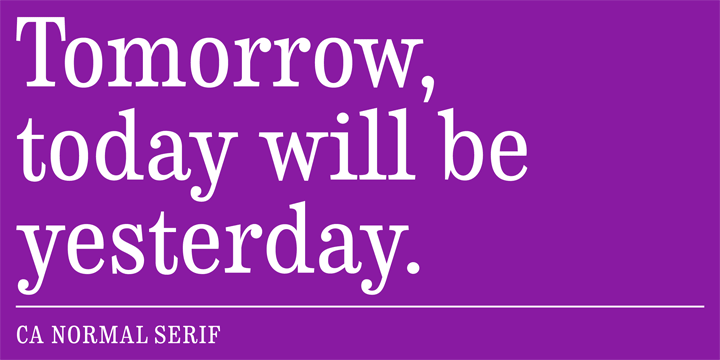
CA Normal bekommt einen Serifen-Bruder, bis 11.8. 50% billiger
CA Normal von der Cape Arcona Type Foundry erhält nun einen Freund/Bruder/Gegenspieler: CA Normal Serif. Anders als bei vielen anderen Meta Familien ist die Normal Serif aber weder eine Renaissance Antiqua, noch wurden wie so oft einfach Serifen an die Groteske angeklebt. Normal Serif bewegt sich irgendwo zwischen Scotch Roman und Slab Serif. Die Einflüsse liegen definitiv im 19. Jahrhundert und bei den Zeitungsschriften von Chauncey Griffith.
Auch ist die Verwandtschaft zwischen der Serif und der Grotesk Normal eher weniger offensichtlich. Trotzdem wird im kombinierten Einsatz deutlich, wie gut die Proportionen zusammen passen und dass sich die beiden Philosophien hervorragend ergänzen. Während die normale Normal den Ansatz verfolgt, eine warme, menschliche statische Groteske zu sein, ist Normal Serif eher härter, steifer und eleganter.